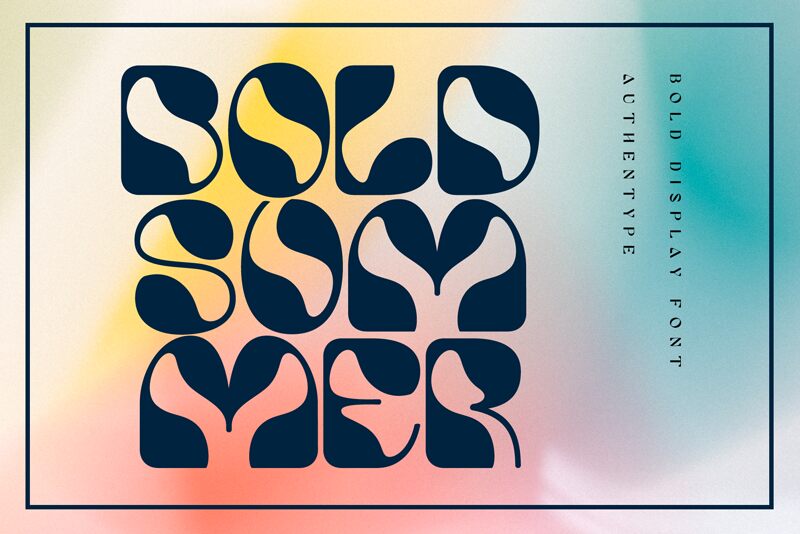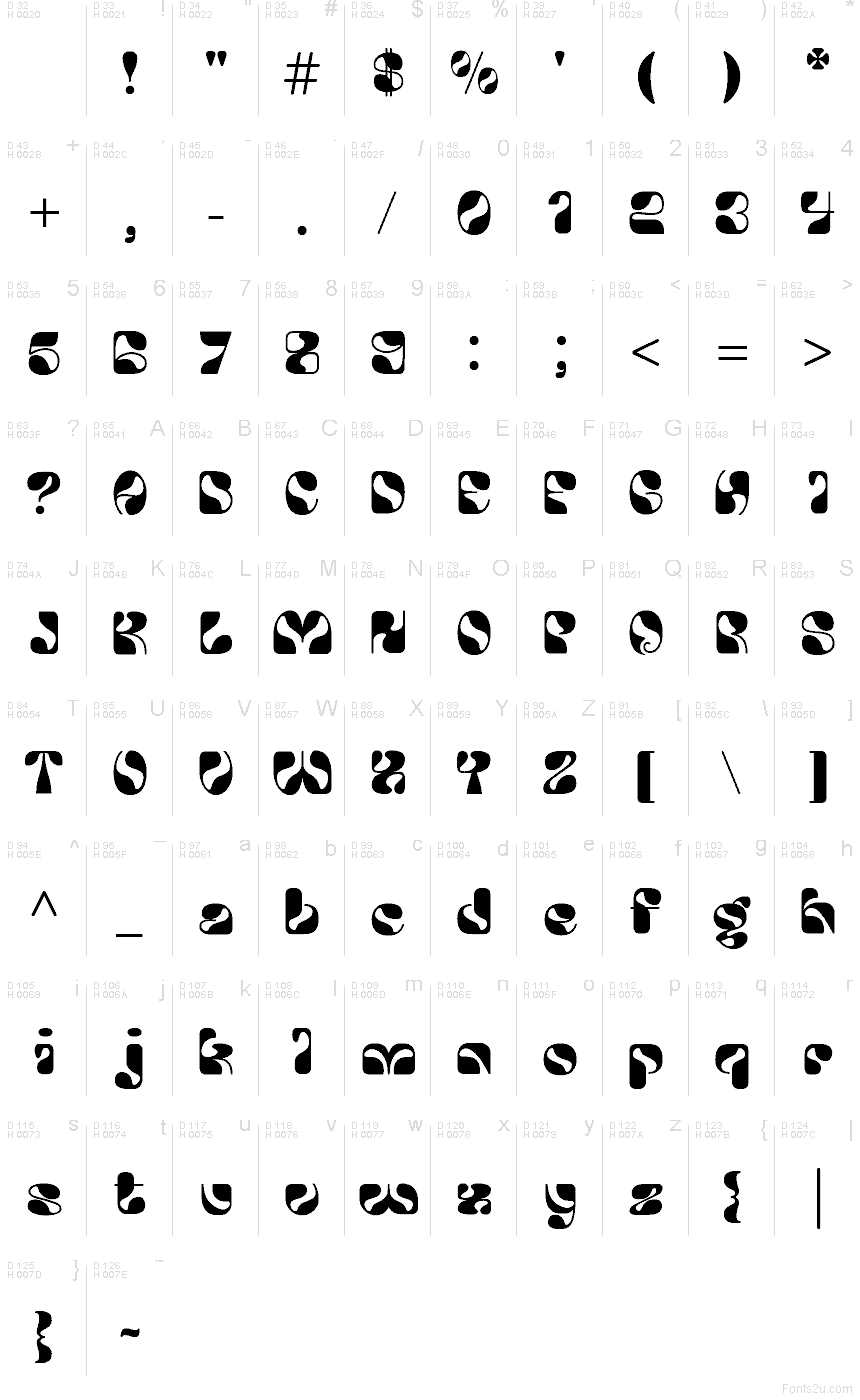
Bold Summer Free 字体
Bold Summer Free
Authentype
Authentype 推出的 Bold Summer 是一款免费的 groovy 风格标题字体,其字形柔和流畅,圆润的线条延展成丝滑的弧度。该设计散发着 70 年代悠闲的韵律,部分字母交织成近乎抽象的环圈,为整套字体赋予了温暖的手工质感。